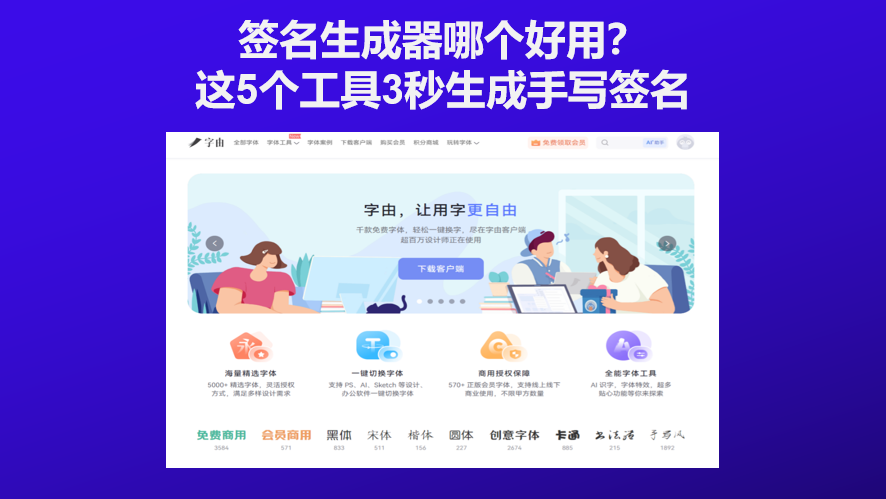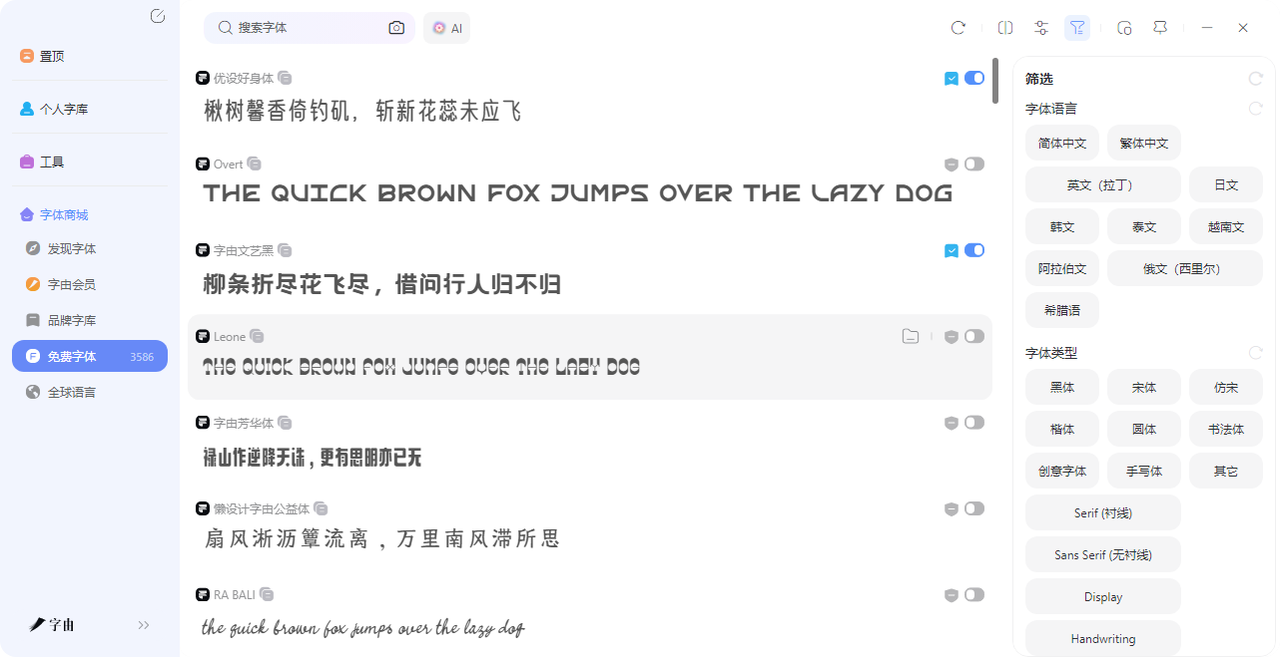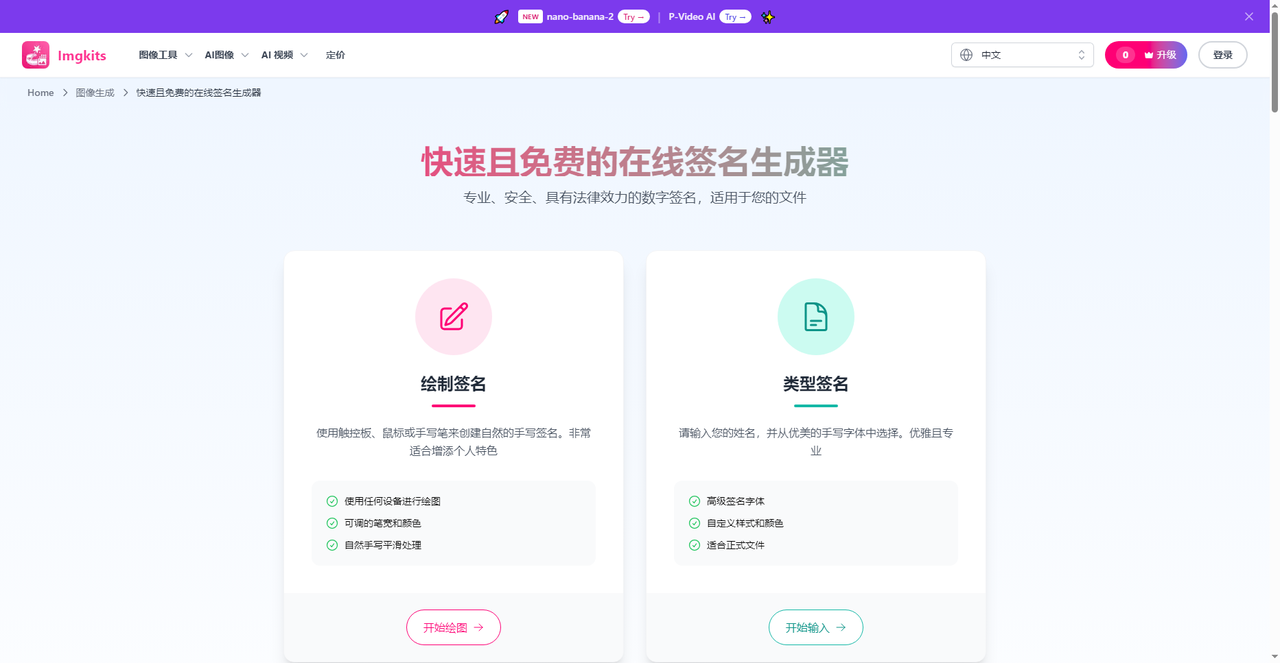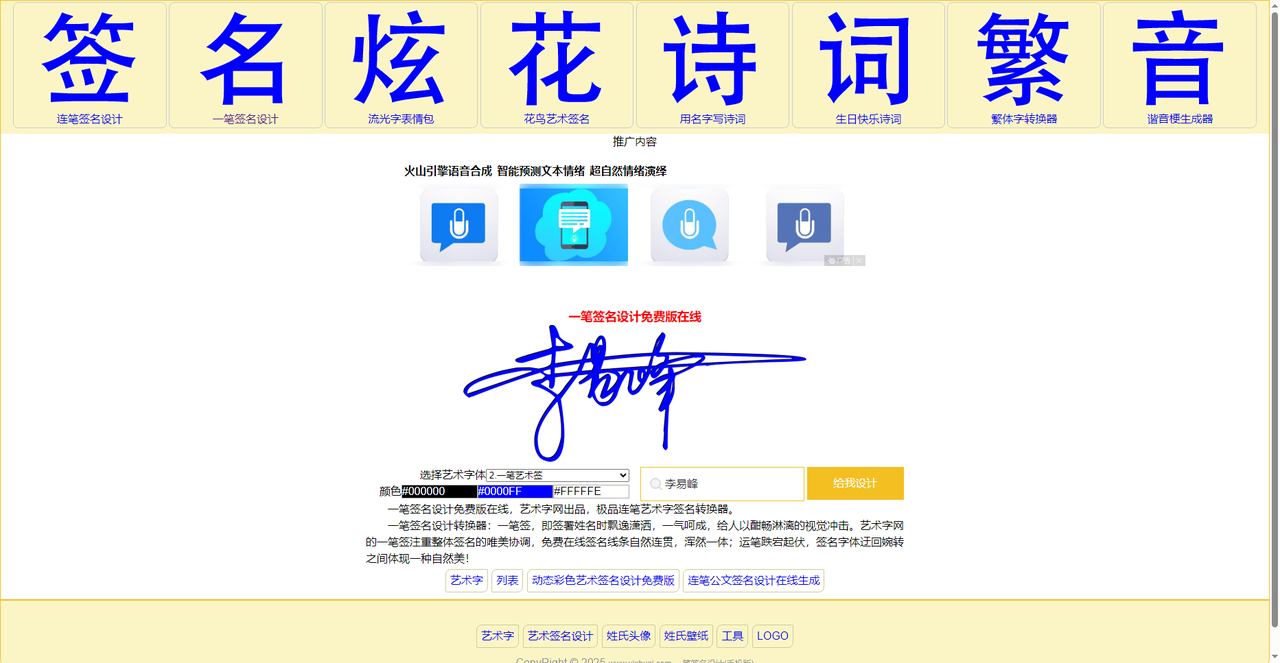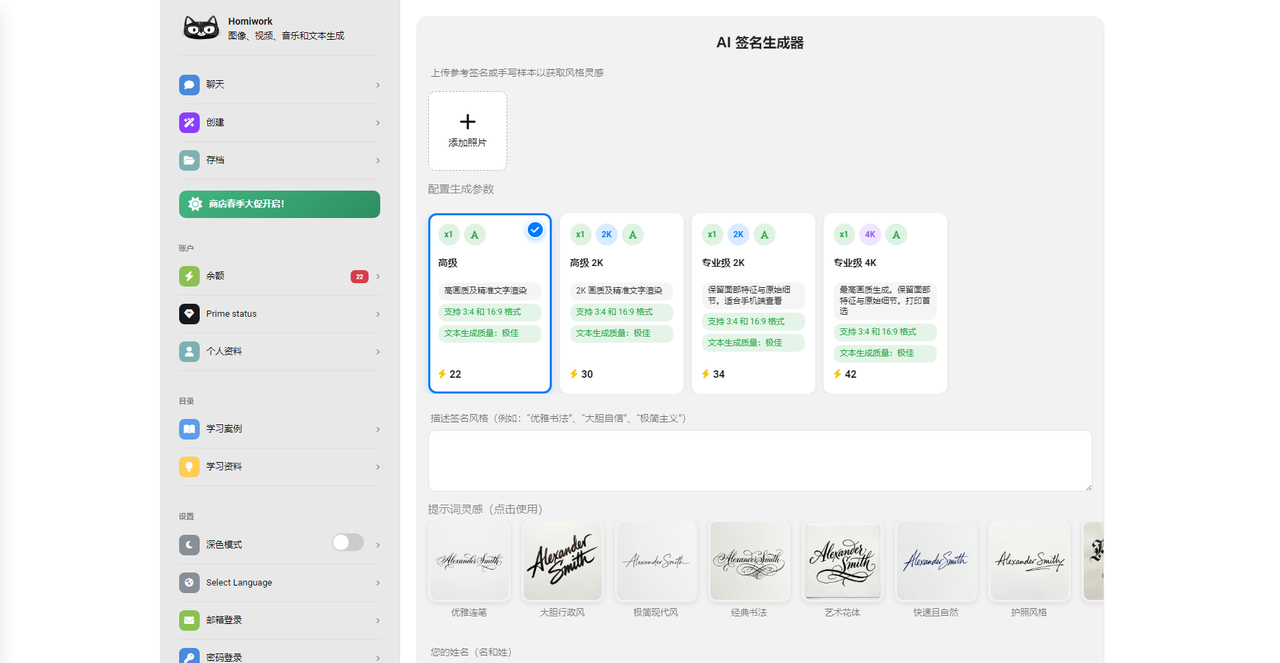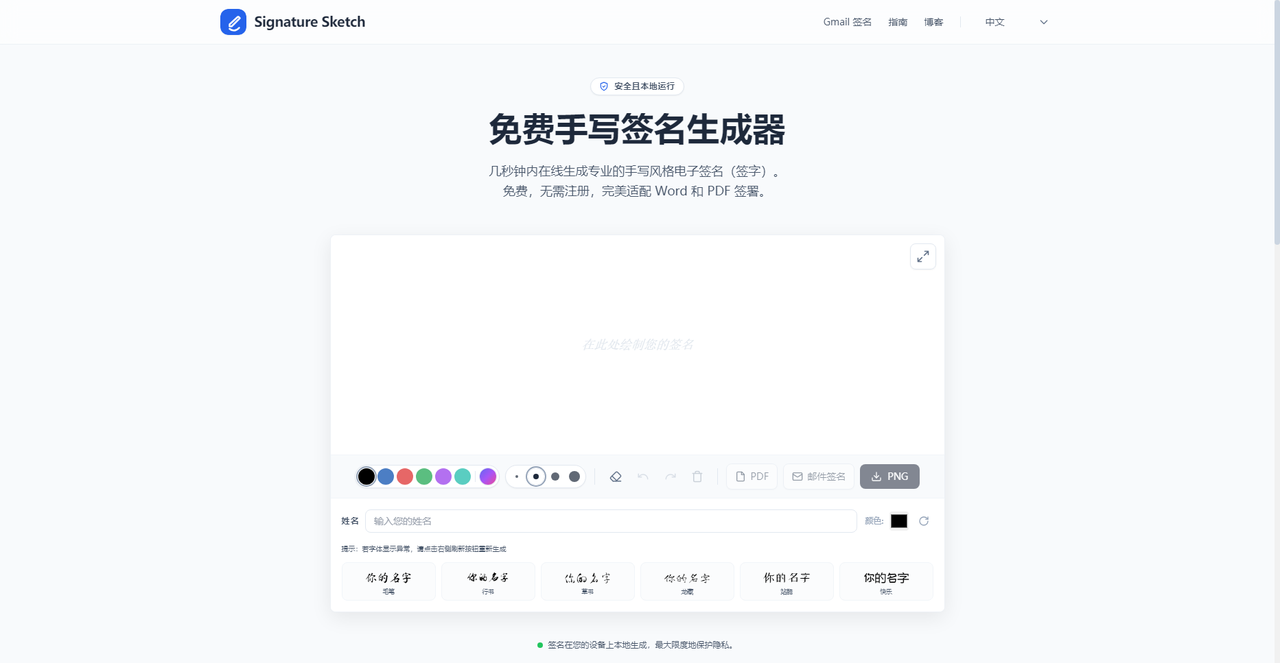
签名生成器哪个好用?这5个工具3秒生成手写签名
以后千万不要在电子合同上用歪歪扭扭的鼠标来写签名了!电子签名能够帮你生成漂亮美观、大方的个人专属签名,这样可以让合同变得正式不少,今天我就整理了 5 个在线签名生成工具,从字由的 AI 字体到手绘板手写签名的 Imgkits,从专注连笔一笔签的艺术字网,到能 AI 模仿笔迹的 Homiwork,再到完全本地运行的隐私优先工具 Signature Sketch。根据自己的需求选一个就行,3 秒生成,打开就能用。
字由是国内最大的字体管理与应用平台之一,注册用户超过 2000 万,和汉仪字库、蒙纳字库等头部厂商深度合作。很多人只知道字由能管理字体,是有用的字体库,但是其实用它来设计签名也相当顺手,有两种不同的途径来生成个性签名:
• 第一种:AI 字体直接生成签名图。 打开字由客户端,找到“工具”下的“AI 字体”,进入后能看到几百款字体特效模板,其中包含大量适合签名的书法风、手写风模板。找到喜欢的模板后,点击“做同款”,在右侧文本框输入自己的名字,点击生成,等 30 秒左右就能得到一张设计好的签名图片。生成后可以下载 PNG 格式,背景透明,直接用在电子文档、合同、简历里。字由每天登录会赠送免费算力,日常生成签名基本不用额外花钱。
• 第二种:从字体库里直接挑合适的字体。 字由拥有超过 10500 款精选字体,包含大量适合签名的书法体、手写体、艺术体。比如“字由芳华体”笔画柔和适合文艺风,“字由文艺黑”既有黑体的稳重又带手写感。在字由客户端里找到喜欢的字体,点一下“激活”,字体就会自动出现在 PS、AI 等软件的字体列表里,打出名字就能直接用。
2、Imgkits
二个工具叫 Imgkits。这是一个免费的在线签名生成器,提供“绘制签名”和“类型签名”两种模式。如果你对自己手写签字还算满意,只是想转成电子版,可以选择“绘制签名”模式——用鼠标、触控板或手写笔直接在画板上手绘签名,支持调节笔触粗细和颜色,还有自然手写平滑处理功能,模拟真实书写手感。如果你手写不好看,或者想直接让 AI 帮你设计,选“类型签名”模式更省事——输入你的姓名,从 26 种高质量手写风格字体中挑选,每种字体都支持调整倾斜度和间距。调完满意了直接导出 PDF 格式,方便直接嵌入合同和电子文档。
3、艺术字网
第三个工具是 艺术字网。这是一个老牌的在线艺术签名生成平台,最大的特色是“一笔签”和“连笔公文签名”。它的“一笔签名设计”采用草书为主、行草为辅的手法,将复杂的名字简化成一两笔写完,线条自然连贯,一气呵成-。如果你名字笔画较多,或者想要那种“行云流水”的签名风格,艺术字网的连笔签名比大多数 AI 生成的效果更自然流畅。操作也很简单:打开网页,在签名设计页面输入姓名,选择想要的字体风格(比如一笔艺术签),点击生成就能预览,下载下来就能用-。免费生成,像素清晰度也够日常使用。
4、Homiwork:AI
第四个工具是 Homiwork。这是一款 AI 驱动的多功能创作 App,签名生成是它众多 AI 功能之一。Homiwork 的签名功能最有意思的地方是“AI 模仿笔迹”。你可以先用手写笔在纸上写一个签名样本,拍照上传,AI 会自动分析你的书写风格,然后生成与你的真实笔迹高度一致的 AI 签名模型。这对那些需要经常签署合同、文件的人来说非常实用——你不需要每次都手写,用 AI 生成的电子签名就能保持一致风格。Homiwork 支持手机端使用,App 上就能生成签名并下载,方便随时调用。
5、Signature Sketch
第五个工具是 Signature Sketch。如果你对数据隐私比较敏感,或者不想注册任何账号,这个工具是最让人放心的选择。Signature Sketch 是一个完全免费的开源签名生成工具,最大的特点是 100% 在浏览器本地运行,所有签名绘制和数据都不会上传到任何服务器。你用鼠标或触控板手绘签名后,可以直接下载透明背景的 PNG 图片,或者生成 PDF 文件,也可以制作带手写签名的邮件签名档。
这几个签名生成器各有各的用法。字由的 AI 字体模板最丰富,适合想要多种签名风格的人;Imgkits 支持手绘和打字两种模式,还直接出 PDF,适合处理正式合同;艺术字网的连笔签名最飘逸,适合喜欢传统书法感的人;Homiwork 能模仿你的真实笔迹,适合需要统一签名风格的人;Signature Sketch 纯本地运行,适合注重隐私的人。选哪个取决于你当下的需求——是要 AI 帮你设计,还是要自己手绘;是处理正式合同,还是日常用用。这几个工具都是免费的,挨个试一遍,3 秒出图,总能找到一款你满意的签名。